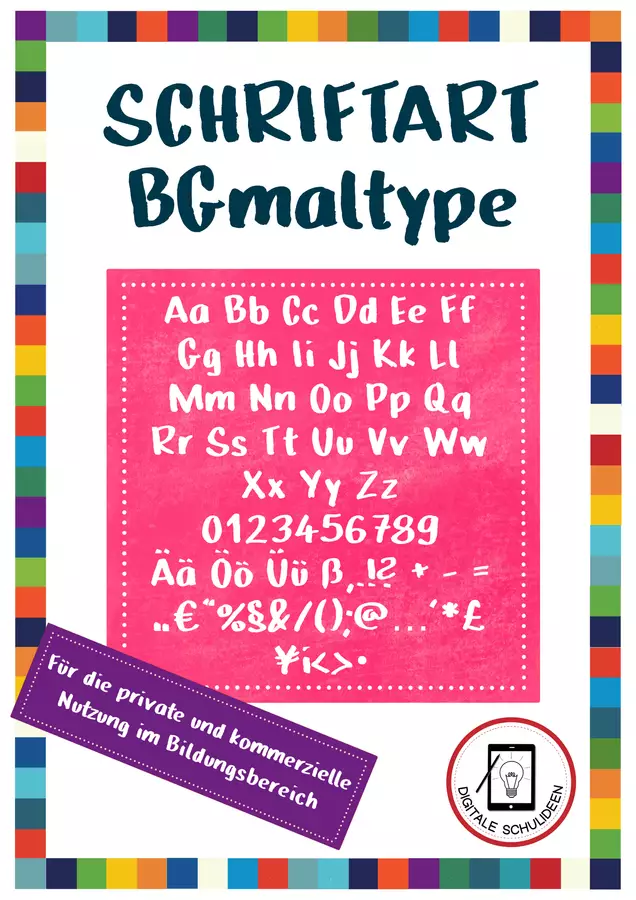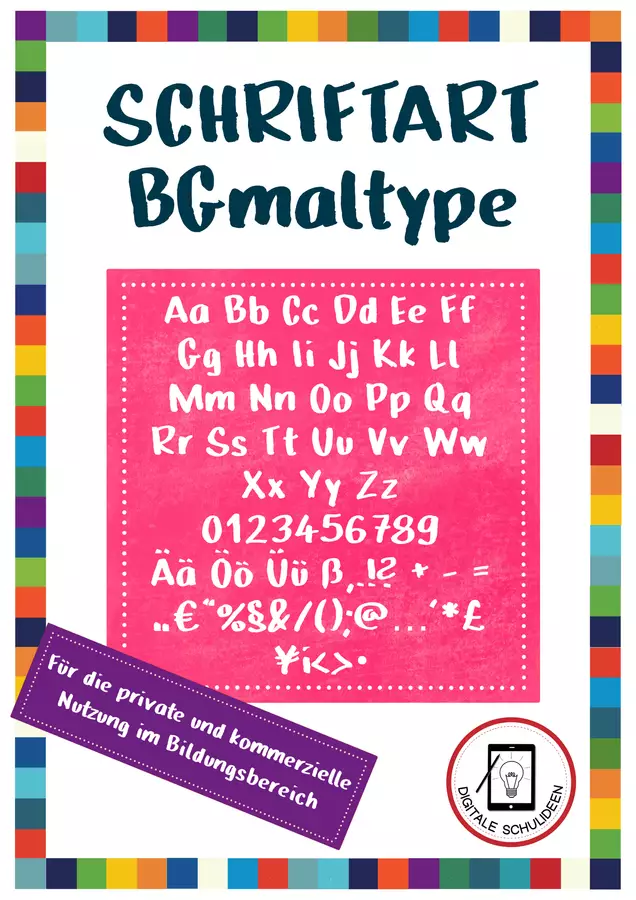
Schöne Schrift
Die Schrift ist für die Kinder gut lesbar und doch besonders. Sie gefällt mir sehr gut.
tolle Schriftart
Super für eigenes Unterrichtsmaterial
Die Schrift ist gut lesbar und super zur Materialerstellung geeignet. Danke!
Praktische Schriftart für den Unterricht und kommerzielle Nutzung
Die Schriftart BGmaltype ist eine großartige Ressource, die sich sowohl für den Unterricht als auch für kommerzielle Projekte eignet. Sie bietet eine klare, gut lesbare Schrift, die in verschiedenen Materialien gut zur Geltung kommt. Besonders praktisch ist die Lizenz für die kommerzielle Nutzung, die es ermöglicht, die Schrift in eigenen Projekten zu verwenden. Sehr empfehlenswert für die Erstellung von Eduki-Materialien👍🏼
Schöne Schriftart
Wieder eine sehr schöne Schriftart, die ich gerne bei meiner Materialestellung verwende.